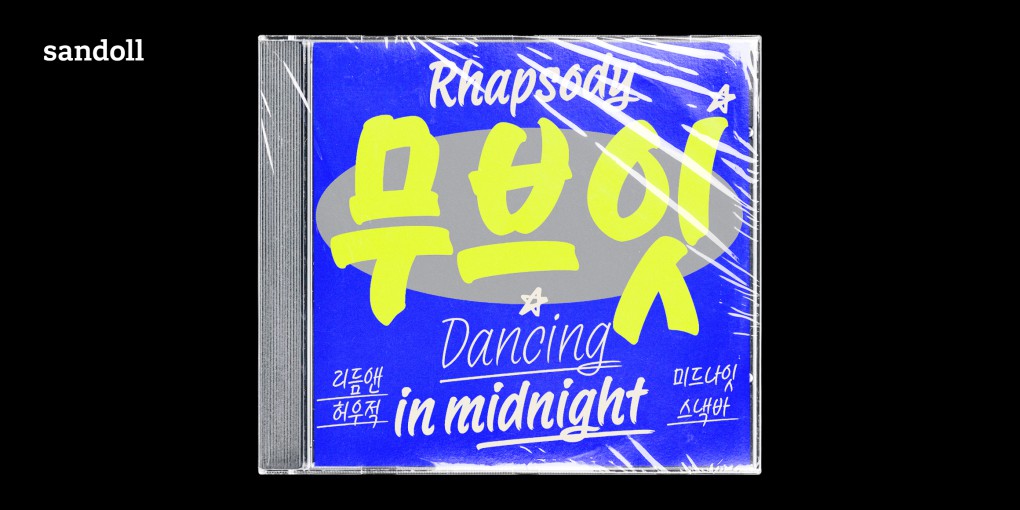
필기구의 특성을 그대로 힙한 캘리그래피 폰트, 「SD 무브잇」
「SD 무브잇」, 어떤 폰트인가요?
「SD 무브잇」은 손의 운동성을 담은 현대적이고 캐주얼한? 힙한! 캘리그래피 폰트입니다. 웨이트 별로 플러스펜, 컴퓨터 사인펜, 브러시 마커 그리고 브로드닙 마커 이렇게 4가지 필기구를 표현했어요! 웨이트 별로 적용해 보시면 그 차이가 느껴지실 거에요. 각각의 필기구를 사용했을 때의 질감과 손의 움직임을 가능한 사실적으로 담고 싶어서, 직접 종이 위에도 써보고 타블렛으로도 써보고 많은 기획 과정을 거쳤네요
「SD 무브잇」, 어디에 사용하면 좋을까요?
「SD 무브잇」은 사실적이고 감성적인 캘리그래피와 잘 정돈된 귀여운 손글씨 폰트 사이의 어딘가에 위치하는 듯해요. 따라서 더욱 다양한 곳에 사용할 수 있죠! 힘찬 슬로건이 들어간 캠페인 그래픽이나, 뮤직비디오와 브이로그의 커다란 타이틀에도 잘 어울리겠어요!
「SD 무브잇」은 4가지 다른 필기구의 특성을 반영한 폰트이기 때문에, 필기구의 질감을 어떤 방향으로 도식화할지 고민이 많았다고 하는데요, 고민 끝에 만화나 일러스트에서 사물을 단순화하고 과장하는 ‘데포르메’ 기법을 사용했다고 하는데요, 장난스럽고 일러스트적인 인상을 더해 준 비결이 무엇인지, 아래 영상을 통해 만나보세요!